El nuevo ícono Font Book de Apple inquieta a los diseñadores
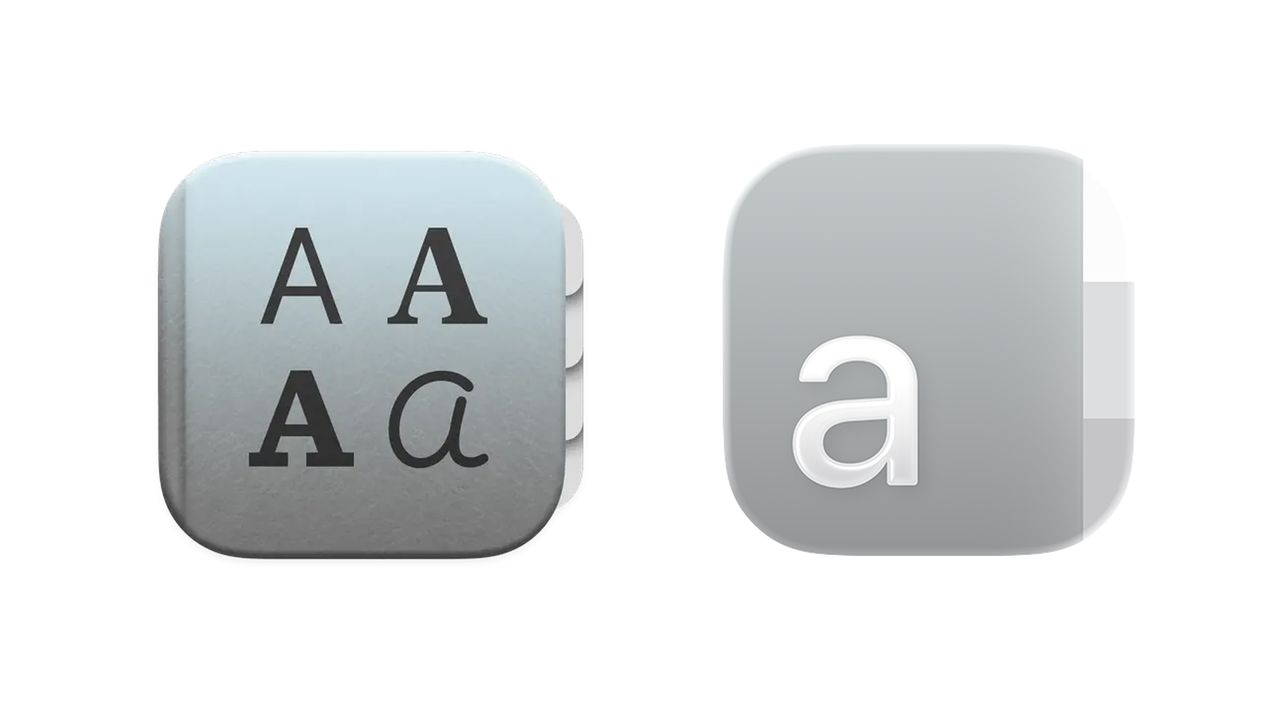
la apariencia de manzanaEl lenguaje de diseño Liquid Glass ha demostrado ser uno de los desarrollos de interfaz de usuario más controvertidos de los últimos años, y quizás el más importante desde entonces. sistema ios 7 En 2013, se produjo un cambio del esqueuomorfismo al diseño plano.
Liquid Glass ha introducido cambios radicales en el diseño de iconos en toda la gama de software de Apple, incluidos macOS e iOS. Si bien los problemas más importantes relacionados con la accesibilidad y la estética irritan a la mayor parte de la oposición, hay un ícono en particular que preocupa a los diseñadores gráficos.
Los iconos de Font Book, el administrador de fuentes integrado de macOS, se han simplificado enormemente. Las diversas fuentes que representan la letra “A” desaparecieron y fueron reemplazadas por un carácter sans-serif limpio.
Mucha gente se quejó de que el propósito de la aplicación ya no estaba claro. “Entiendo la versión moderna, pero esto es decepcionante, prefiero que diga ‘Aa’ en lugar de solo ‘a'”, comentó un usuario de Reddit. Otro añadió: “Bueno, sí, eso es inquietante”.
Pero no todo el mundo odia el diseño limpio. “Si bien la aplicación anterior comunicaba mejor el propósito y la identidad de la aplicación, encuentro la nueva aplicación más bonita. Considerando todo, diría que ambas son buenas en diferentes maneras”, comentó otro usuario.
Para nosotros, un diseño más limpio no es necesariamente una degradación y ciertamente se adapta a la estética de Liquid Glass. Pero podría decirse que el diseño de Apple es mejor cuando es divertido, y esto representa otro pequeño pero decepcionante alejamiento del diseño tradicional.Manzanas coloridas de los años 90.